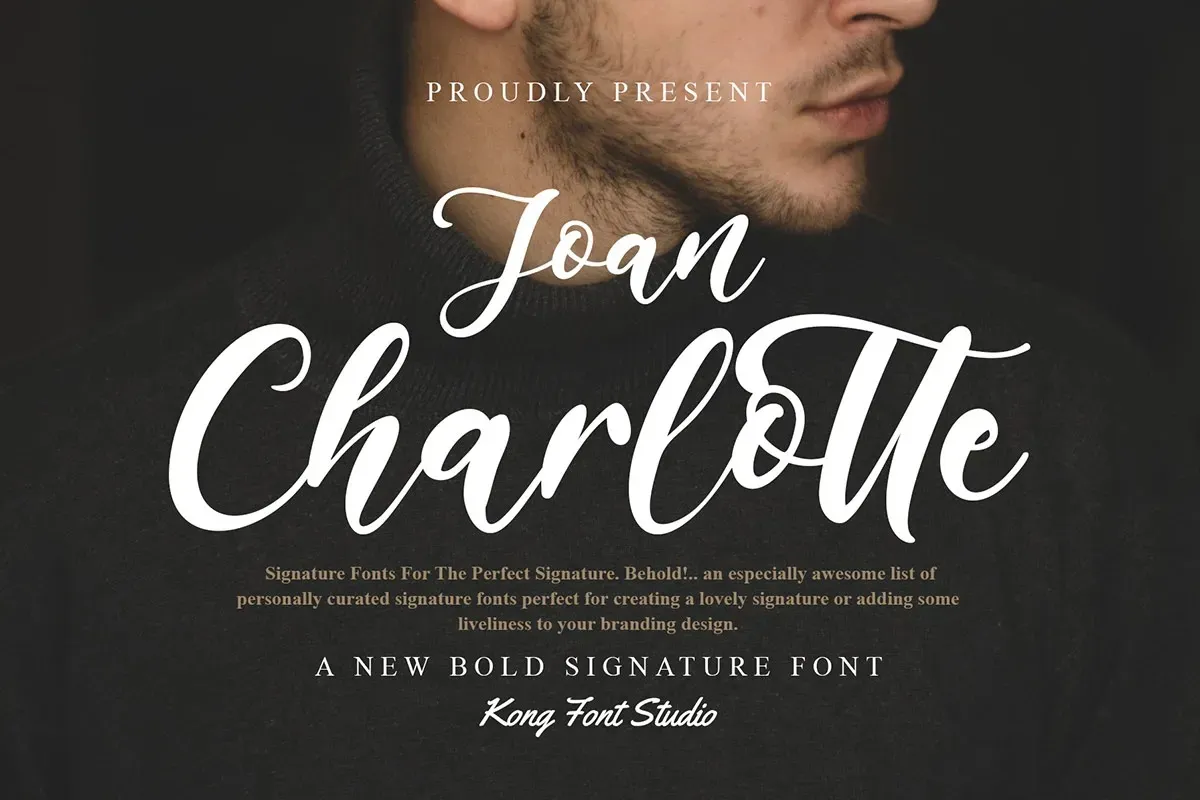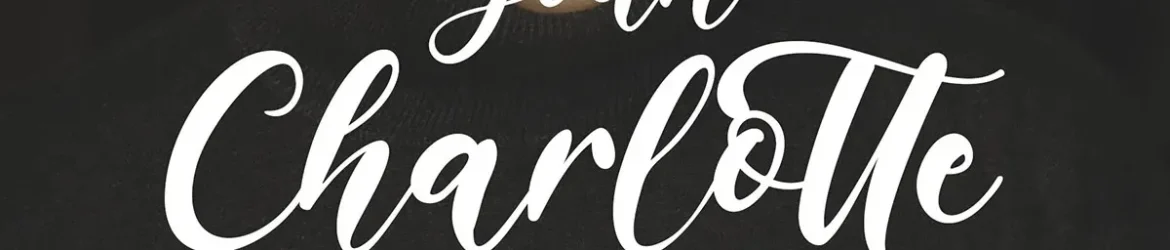
Joan Charlotte é uma elegante fuente cíliada que oferece um estilo sofisticado, feminino e nobre, mantendo ao mesmo tempo uma atmosfera amigável. Perfeita para aplicações como moda, identidade de marca, blogs em tendências ou boutiques de casamento, ela também se destaca para qualquer negócio que deseja adquirir um visual luxuoso, chic e elegante. Este script cíliado não apenas impressiona pela sua aparência envolvente e sofisticada, mas também por sua versatilidade, tornando-se uma escolha inteligente para uma ampla gama de projetos, desde anúncios até design editorial. A Joan Charlotte é uma fonte que se destaca na categoria dos tipos de escrita, oferecendo uma combinação única de elegância e conforto atraente.